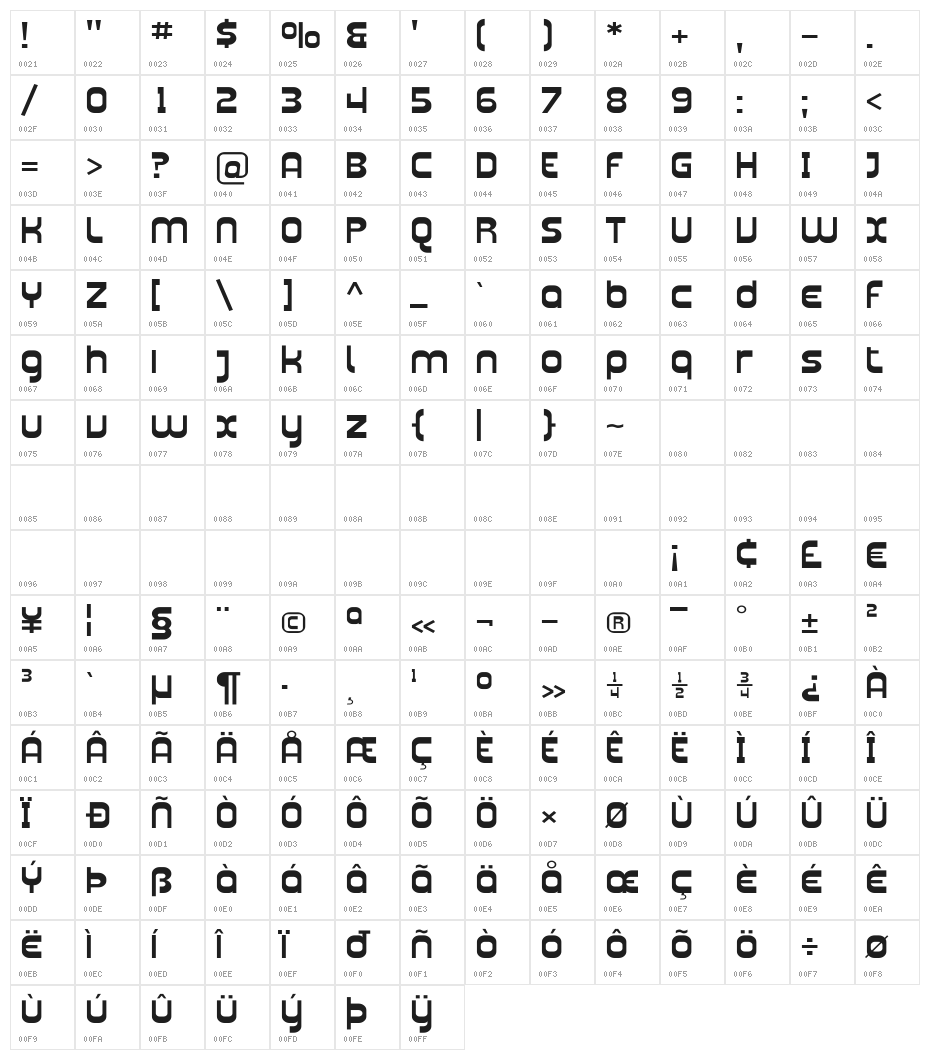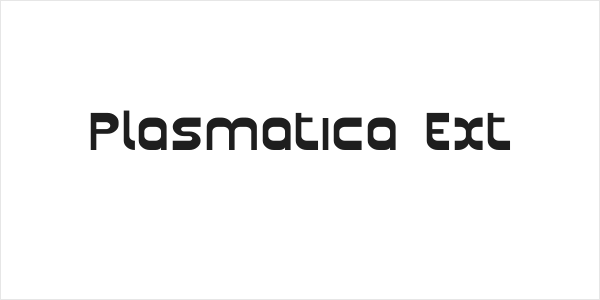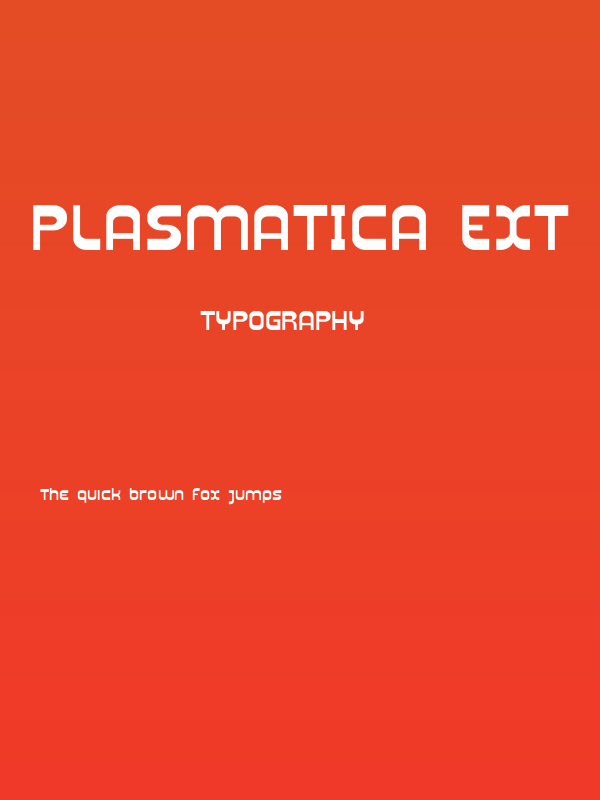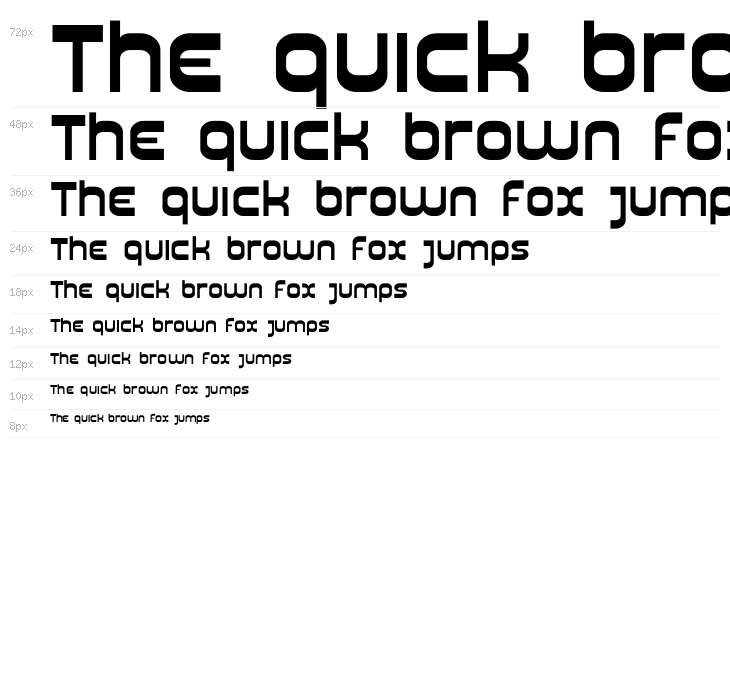
Plasmatica Ext Font
| Categorie | Modern |
| Caso d'uso | Headlines, Logos, Digital media |
| Progetti proposti | Ideal for technology branding, sci-fi posters, video game titles, and modern advertising. |